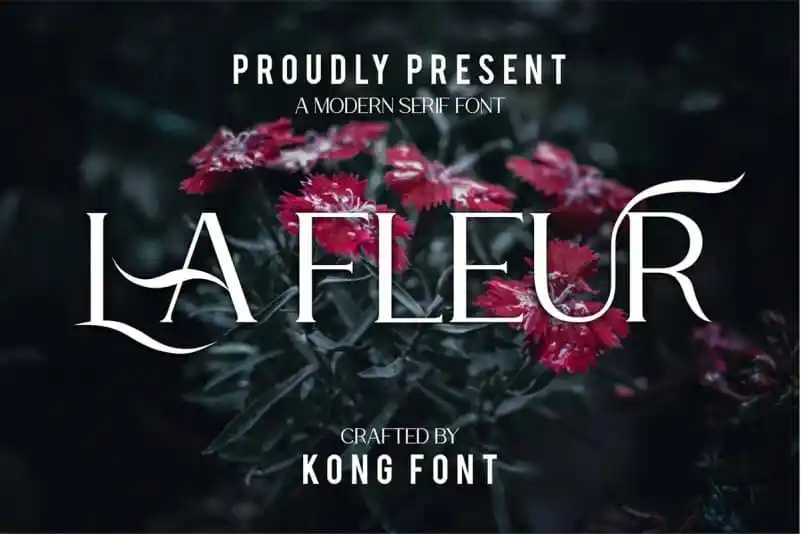
La Fleur Serif Font – Download Grátis
La Fleur Serif é uma fonte serif moderna com toques vintage que traz alternativas estilizadas e ligaturas cortadas a fio para tornar seu design ainda mais elegante. Esta fonte foi criada pela fontkong, um designer do 99designs dedicado à criação de belas alternativas estilizadas e ligaturas. Ideal tanto para uso em texto quanto para aplicações de exibição visual, La Fleur Serif oferece uma escolha única. Suas alternativas estilizadas e ligaturas criam um equilíbrio harmônico entre modernidade e elegância do design serif clássico. É perfeita para criar texturas interessantes em portfólios de trabalhos, gráficos corporativos ou qualquer aplicação que exija uma sensação moderna e sofisticada no design da sua marca.